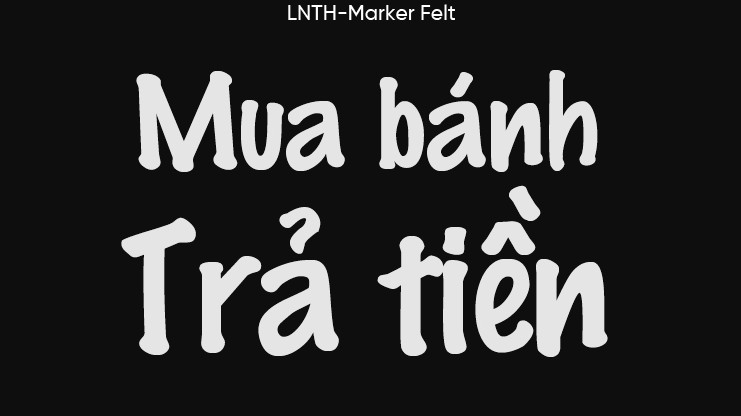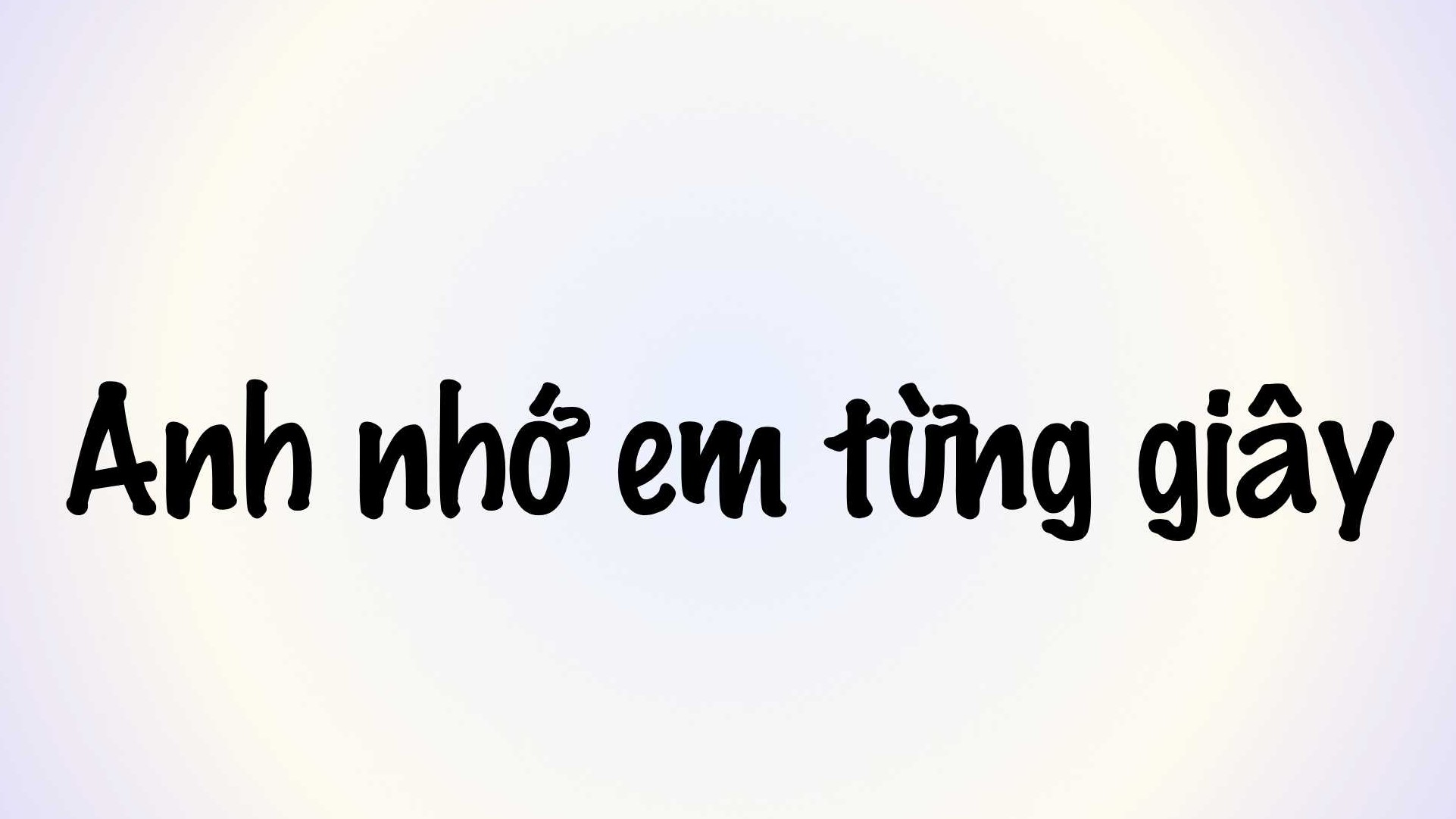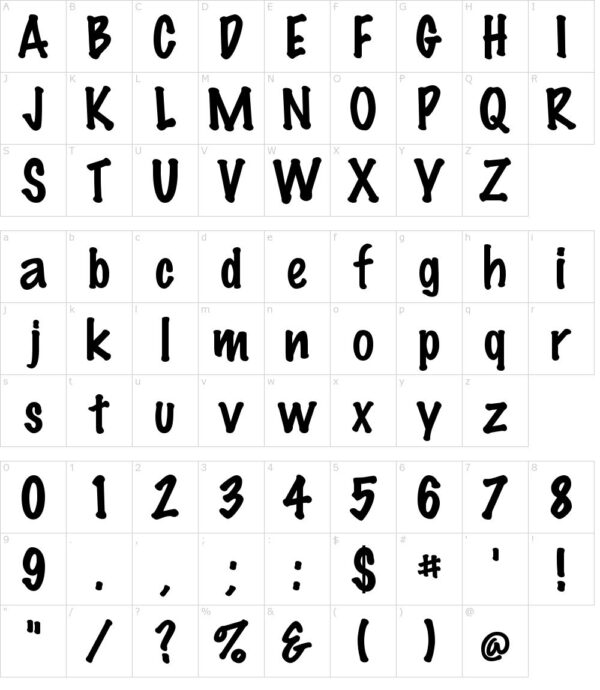
Marker Felt Font Việt hóa là bộ phông chữ thuộc dòng Casual Display mô phỏng chân thực nét viết của ngòi bút lông dạ dầu trên giấy phác thảo hoặc bảng trắng. Với các đường nét bo tròn tự nhiên, độ dày đồng đều và cảm giác phóng khoáng, kiểu chữ này giúp các kiến trúc sư, nhà thiết kế mang lại sự gần gũi, tươi vui cho các bản vẽ phác thảo ý tưởng, bảng thực đơn quán cà phê container hay biển chỉ dẫn góc học tập trong nhà lắp ghép.
Nét bút dạ tự nhiên và phong cách phác thảo gần gũi của Marker Felt Font Việt hóa
Điểm cuốn hút của Marker Felt Font Việt hóa nằm ở sự không cầu kỳ trong cấu trúc hình thể, gợi nhớ đến những nét vẽ tay ghi chú nhanh của kỹ sư tại công trường. Đầu nét chữ tròn trịa và tỷ lệ các con chữ có sự xê xích nhẹ nhàng mang lại nhịp điệu sinh động, loại bỏ hoàn toàn sự cứng nhắc của các phông chữ kỹ thuật thông thường.
Sự ổn định về mặt thị giác của dòng font này giúp truyền tải thông điệp một cách chân thành, mộc mạc và dễ tiếp cận. Khi xuất hiện trên các bề mặt vật liệu kiến trúc như bảng đen viết phấn, gỗ ép sáng màu hay vách panel sơn màu sắc tươi tắn, Marker Felt tạo nên cảm giác thân thiện, làm giảm bớt tính chất lạnh lùng của các hệ kết cấu kim loại xây dựng.
| Phân loại phong cách | Casual Display / Marker Handwritten / Sketch |
| Mục đích phù hợp | Ghi chú bản vẽ phác thảo, biển menu, decor |
Tư vấn từ chuyên viên: Marker Felt sở hữu nét chữ dày và phong cách viết tay tự do. Để bản thiết kế đạt hiệu quả thẩm mỹ tốt, bạn nên sử dụng phông chữ này cho các ghi chú ý tưởng, tiêu đề bảng tin hoặc tên khu vực chức năng. Phần nội dung mô tả kỹ thuật chi tiết nên đi kèm một phông chữ không chân thanh mảnh hơn để người xem tiếp nhận thông tin dễ dàng.
03 Ứng dụng phông chữ Marker Felt vào công trình thực tế
Nhờ vẻ ngoài mộc mạc và tính gợi hình phong phú, bộ phông chữ này mang lại giá trị thực tế cao trong khâu tạo điểm nhấn cho các công trình hiện đại:
- Ghi chú phác thảo ý tưởng trên Bản vẽ Kiến trúc: Sử dụng tải font chữ Marker Felt việt hóa cho các mũi tên chỉ dẫn, ghi chú vật liệu trên phối cảnh 3D giúp bản vẽ trông như một cuốn nhật ký thiết kế thủ công đầy tính tâm huyết.
- Hệ thống biển Menu cho Quán Cafe Container: Những nét bút dạ dày dặn rất ăn ý khi in ấn trên decal dán bảng đen hoặc tấm mica trong suốt, tạo nên diện mạo trẻ trung, kích thích sự tò mò của khách hàng ghé thăm thưởng thức đồ uống.
- Trang trí không gian lớp học và góc sáng tạo của bé: Bạn có thể dùng phông chữ này để in tên phòng, biển nội quy thân thiện hoặc làm bảng phân công trực nhật trong các trường mầm non lắp ghép, mang lại không gian học tập sinh động cho các bạn nhỏ.
03 Lưu ý bố cục tải font Marker Felt việt hóa luôn rõ ràng và sinh động
Để khai thác hiệu quả vẻ đẹp của dòng font bút dạ này mà không gây cảm giác lộn xộn cho bản vẽ, người thiết kế nên lưu tâm một số kinh nghiệm sau:
- Kiểm soát mật độ chữ: Do nét bút dạ có độ chiếm diện tích bề mặt lớn, bạn nên hạn chế nhồi nhét quá nhiều chữ trong một khung hình hẹp. Hãy phân bố các dòng chữ thông thoáng để nét bo tròn của ký tự được hiển thị rõ ràng.
- Bố trí khoảng cách dòng: Nên thiết lập khoảng cách giữa các dòng văn bản rộng hơn một chút so với phông in ấn thông thường để các dấu thanh tiếng Việt không bị chạm vào chân chữ của dòng phía trên.
- Phối hợp cùng màu sắc tương phản: Marker Felt phát huy hiệu quả thị giác cao khi đặt trên các nền màu đơn sắc sáng (như vàng nhạt, trắng kem) với nét chữ đen, hoặc ngược lại nét chữ trắng trên nền bảng đen, tạo cảm giác viết phấn sinh động.
FAQs – Thắc mắc thường gặp khi sử dụng phông chữ Marker Felt
1. Font Marker Felt có dùng được trên ứng dụng Canva không?
2. Phông chữ này có hỗ trợ đầy đủ các biến thể đậm nhạt không?
Bộ phông Marker Felt thường cung cấp hai biến thể thông dụng là Thin (nét mảnh như bút dạ kim) và Wide/Bold (nét dày đậm như bút lông bảng), hỗ trợ bạn linh hoạt phân cấp thông tin theo nhu cầu thiết kế.